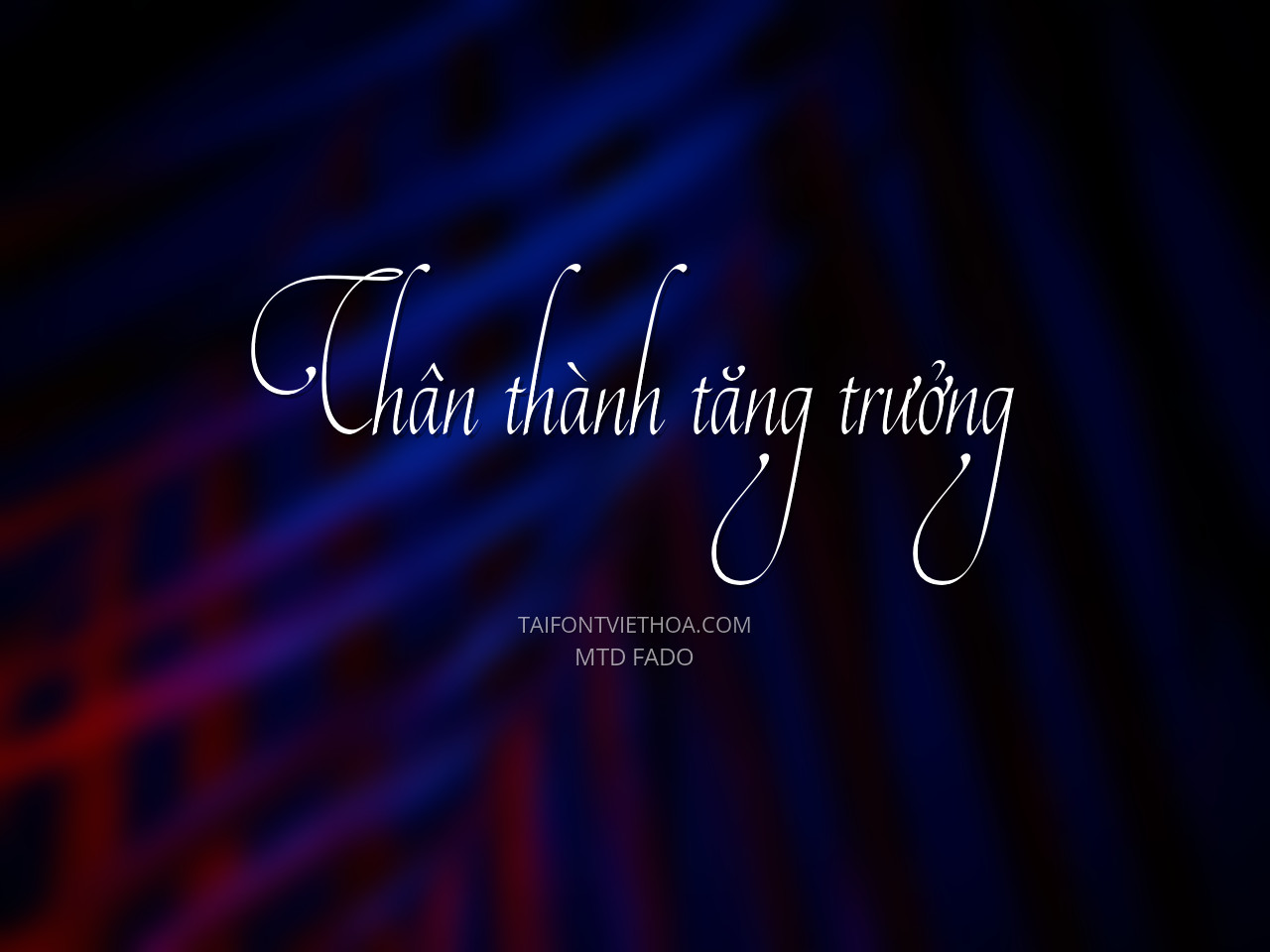
Font việt hóa MTD Fado
Tác giả Font: Olga Umpeleva
Giới thiệu về font Fado
Fado là một font chữ viết tay hiện đại mang phong cách đơn giản, cá tính và phóng khoáng, được thiết kế bởi Motokiwo Type (MTD). Lấy cảm hứng từ sự tự do trong ngôn ngữ biểu cảm và cái đẹp của sự không hoàn hảo, Fado tạo nên một bản sắc riêng biệt với những nét chữ mạnh mẽ nhưng vẫn đầy mềm mại. Font mô phỏng nét bút tự nhiên, giúp truyền tải cảm xúc chân thật trong thiết kế. Phiên bản Việt hóa do chính MTD thực hiện, hỗ trợ đầy đủ tiếng Việt và hơn 70 ngôn ngữ khác, phù hợp cho các dự án mang tính toàn cầu.
Đặc điểm thiết kế và ứng dụng của font Fado
Fado sở hữu các nét bút viết tay đậm – nhạt linh hoạt, với độ nghiêng nhẹ và các đoạn chuyển nét tinh tế. Font tạo cảm giác như được viết nhanh nhưng đầy cảm xúc, mang lại vẻ sống động, gần gũi và cá tính cho văn bản. Nhờ tính năng OpenType với nhiều ligatures và ký tự thay thế, Fado cho phép người dùng biến tấu sáng tạo mà không lo trùng lặp hay nhàm chán.
Ứng dụng lý tưởng: thiết kế logo cá nhân, bao bì sản phẩm handmade, tiêu đề poster, blog thời trang, bìa sách sáng tạo, thiệp mời sự kiện, sticker, hoặc các nội dung mạng xã hội mang phong cách cá nhân. Ngành nghề phù hợp: thời trang, mỹ phẩm thủ công, thiết kế nghệ thuật, studio ảnh, wedding planner, quà tặng sáng tạo và thương hiệu cá nhân hóa.